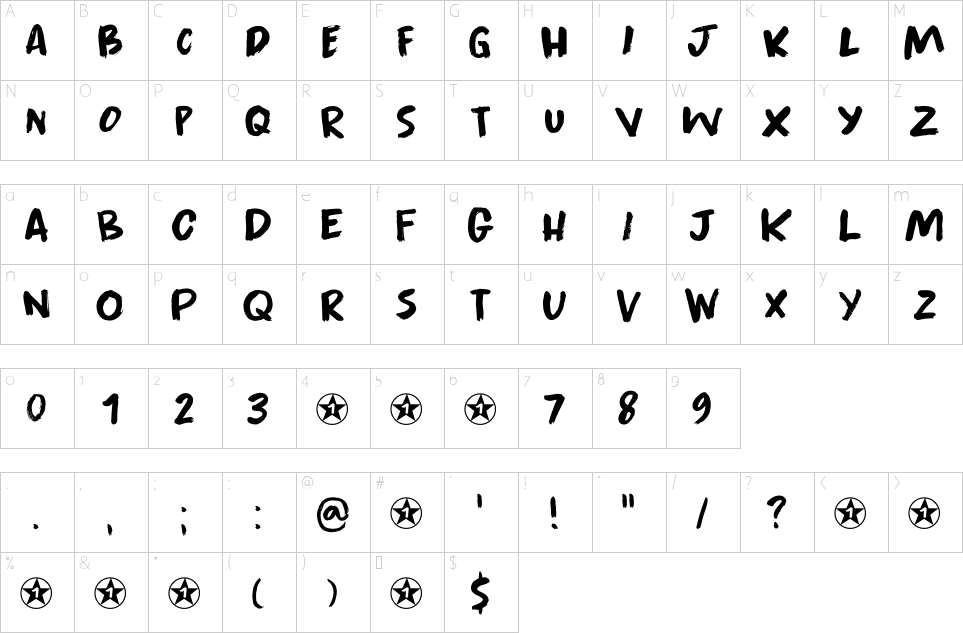
A Apex Brush é uma fonte brush que foi desenhada por Hanoded e já foi baixada 12.619 vezes. Ideal para dar um toque especial em design gráfico, gravações de vídeo ou até mesmo em escrita diária, esta fonte combina facilidade de uso com um toque criativo. Suas formas arredondadas e seu estilo único oferecem um aspecto único que pode dar um toque especial a qualquer projeto. Seja você um designer gráfico, um videomaker ou até mesmo alguém que gosta de dar um toque especial em suas próprias mensagens escritas, a Apex Brush pode ser o que você precisa. Com versão disponível tanto para Windows quanto para Mac, pode-se garantir uma experiência de uso fluida em praticamente qualquer dispositivo.